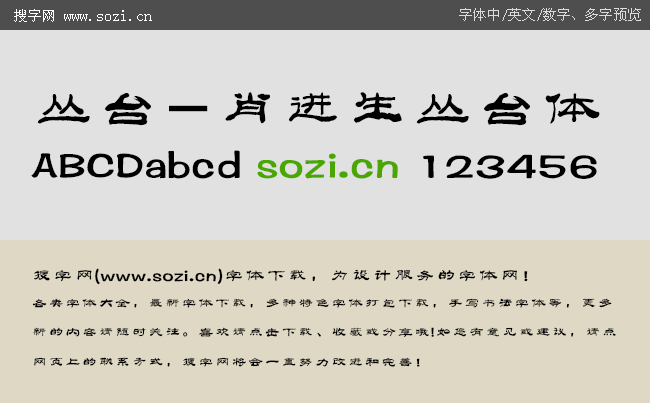
叢臺-肖進(jìn)生叢臺體
搜字網(wǎng)提供一款叢臺-肖進(jìn)生叢臺體中文書法字體下載,叢臺-肖進(jìn)生叢臺體是一款手寫風(fēng)格的書法字體,字體整體效果非常出色,適合應(yīng)用于廣告設(shè)計、名片設(shè)計、包裝印刷、產(chǎn)品設(shè)計等應(yīng)用。搜字網(wǎng)提供一款大梁體繁簡精全